亥年のゆる文字年賀状: 筆ペンで書く
来年の事をいうと鬼が笑うそうだが、猪が突撃してくる事は多分ないだろう。
雑貨デザイナー、イラストレーターとして活躍する宇田川一美氏による、筆ペンによるゆる文字を使用した年賀状と干支の亥(猪)のイラストの描き方が紹介された「亥年のゆる文字年賀状: 筆ペンで書く」が誠文堂新光社から2018年9月7日に発売された。
特別な方へ、心のこもった手書きの年賀状を贈りませんか?
筆ペンで書くゆる文字を使った年賀状と、干支(亥・イノシシ)のイラストの描き方を紹介します。
年賀状に勇ましいイノシシや可愛いうり坊のイラストを添えて、気持ちを伝える作品を掲載。
ゆる文字の基本の書き方は、わかりやすく写真でステップを掲載。
スミの筆ペンや、シチュエーションに応じて色筆ペンを使って、かわいくカラフルに描くものなどを展開します。
味わいあるイラストや文字のテクニックも紹介しています。
著者について
宇田川 一美:雑貨デザイナー、イラストレーター。著書に『筆ペンで書く ゆる文字』、『もっと筆ペンで書くゆる文字 季節のはがき』、『手づくり文房具』、『気持ちを伝える手づくり文房具』等がある。
「ゆる文字」で年賀を書いても〆切は締めていこう!
「ゆる文字」で年賀状を作っても〆切はゆるめずに計画的にどうぞお願いします!
宇田川一美氏のその他の「ゆる文字」著書「書き込み式 ゆる文字練習帖: 暮らしに彩りを添える筆ペン習字 」
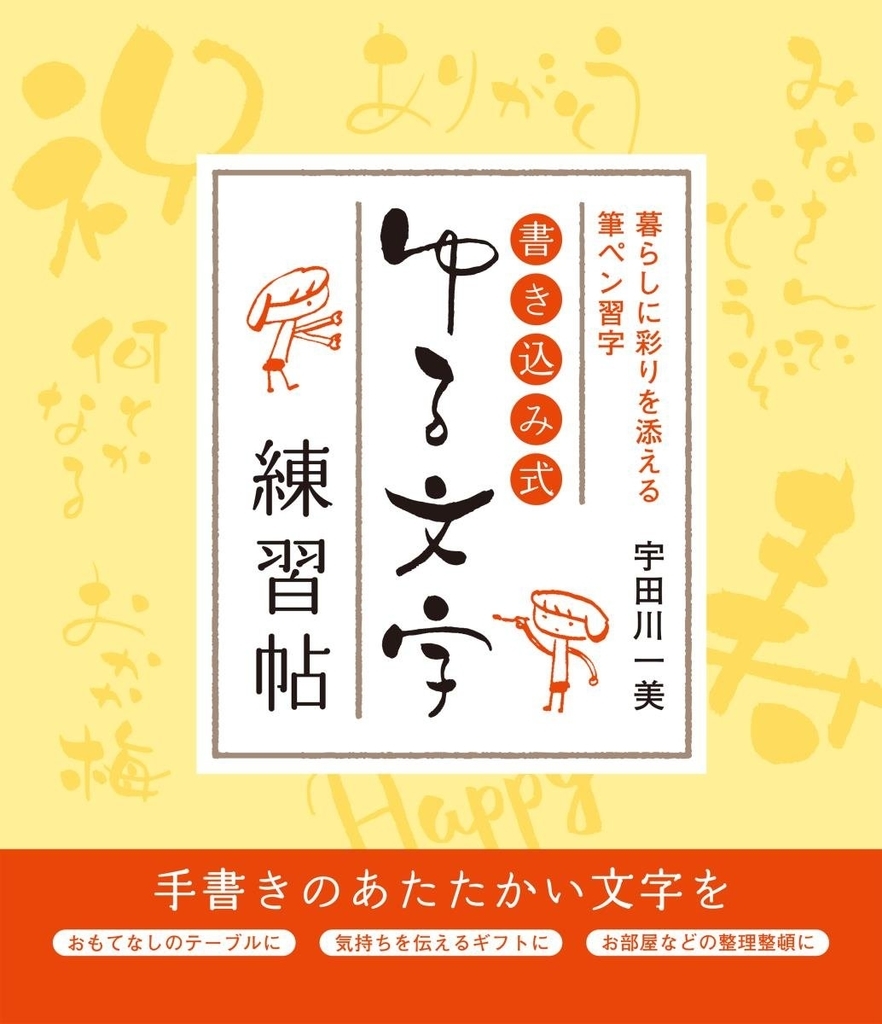
宇田川一美氏著書「書き込み式 ゆる文字練習帖: 暮らしに彩りを添える筆ペン習字」は誠文堂新光社から2017年10月13日に発売された。
筆ペンで書くゆる文字がすらすら書けるようになる、書き込み式の練習帖です。
家族のお弁当や、家のつくりおきの御惣菜、ジャムのビンやおにぎり、来客時のお品書きに添える美味しく見える筆文字の練習や楽しさを表現するコツ、贈り物に便利な祝い事の文字など、暮らし全般に活かせる「ゆる文字」の実用例を多数ご紹介します。
宇田川一美氏のその他の「ゆる文字」著書「もっと筆ペンで書くゆる文字 季節のはがき: 季節を届ける味わい文字」
宇田川一美氏著書「「もっと筆ペンで書くゆる文字 季節のはがき: 季節を届ける味わい文字」は誠文堂新光社から2014年3月17日に発売された。
本書では筆ペンで書くゆる文字をつかった季節のハガキの楽しみ方を紹介します。
文字の書き方は、わかりやすく理論的に解説(ロジックを掲載)。
スミの筆ペン一本でかける味文字をメインとし、
シチュエーションに応じた24色筆ペンでかわいくカラフルに書くものなども展開します。
季節で楽しめる事例や季節の言葉、季節のイラストも多数紹介。
そのまま使える実用例を100個掲載します。
「筆ペンで書く ゆる文字: 贈り物にあいさつ状に最適な文字の形と季節の言葉」
宇田川一美氏著書「「筆ペンで書く ゆる文字: 贈り物にあいさつ状に最適な文字の形と季節の言葉」は誠文堂新光社から2013年9月10日に発売された。
筆ペンで書く、くずし文字の本です。
筆ペンを使った味わい文字の書き方を紹介します。
文字の書き方は、わかりやすく理論的に解説(ロジックを掲載)。
スミの筆ペン一本でかける味文字をメインとし、シチュエーションに応じたカラー筆ペンでかわいくカラフルに書くものなども展開します。
上品さを損なわないデザインで、季節で楽しめる事例や季節の言葉も紹介。
また調味料のビンなどに文字やイラストを書きおしゃれに収納、センスいいインテリアに変身する実用例も掲載します。